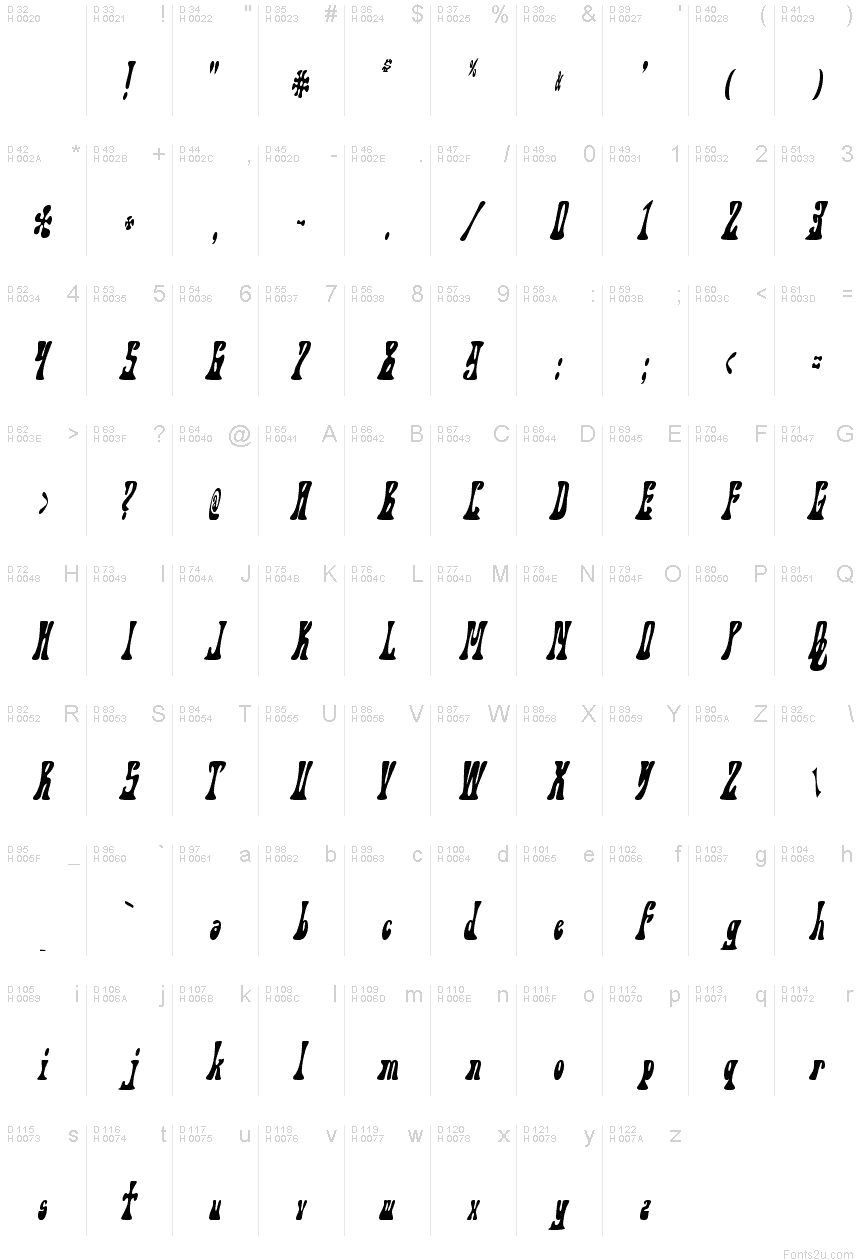
خط Chicken Wire Lady من تصميم Ray Larabie هو خط عرض مجاني بنمط كوميدي، يتميز بتصميم مرن وجريء وقواعد حبرية متجمعة تعطي انطباعاً بأن الحبر قد سال في القاعدة. يبدو كل حرف كأنه ممطوط طولياً ومضغوط عند الأساس، مما يمنح العناوين طابعاً مطاطياً وكأنه مرسوم يدوياً، وهو طابع يجذب الانتباه دون أن يبدو مصقولاً أكثر من اللازم أو رسمياً جداً. الضربات السميكة والإيقاع المتقارب يجعلان الكلمات تبدو كأشكال عضوية بارزة، أشبه بظلال ورق مقصوص ترقص عبر الصفحة.
مع Chicken Wire Lady، ستحصل على صوت عالٍ وغير تقليدي يتألق في ملصقات الحفلات، والمجلات المستقلة (Zines)، ودعوات حفلات الريترو، وقوائم الطعام في المقاهي أو البارات، وأغلفة الألبومات، والشعارات ذات الطابع الغريب. هذا الخط المجاني يبرز جماله بشكل خاص في الأحجام الكبيرة حيث يمكن لخطوطه المتعرجة أن تتنفس حقاً؛ ادمجه مع خط بلا زوائد (Sans Serif) هندسي ونظيف للنصوص الأساسية للحفاظ على القراءة المريحة، مع ترك Chicken Wire Lady يتولى مهمة جذب الأنظار.